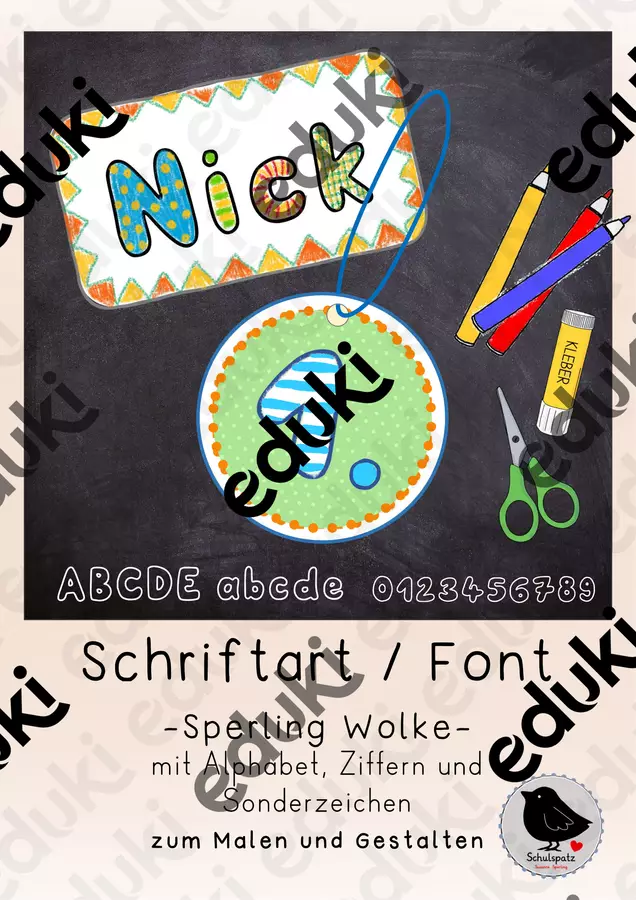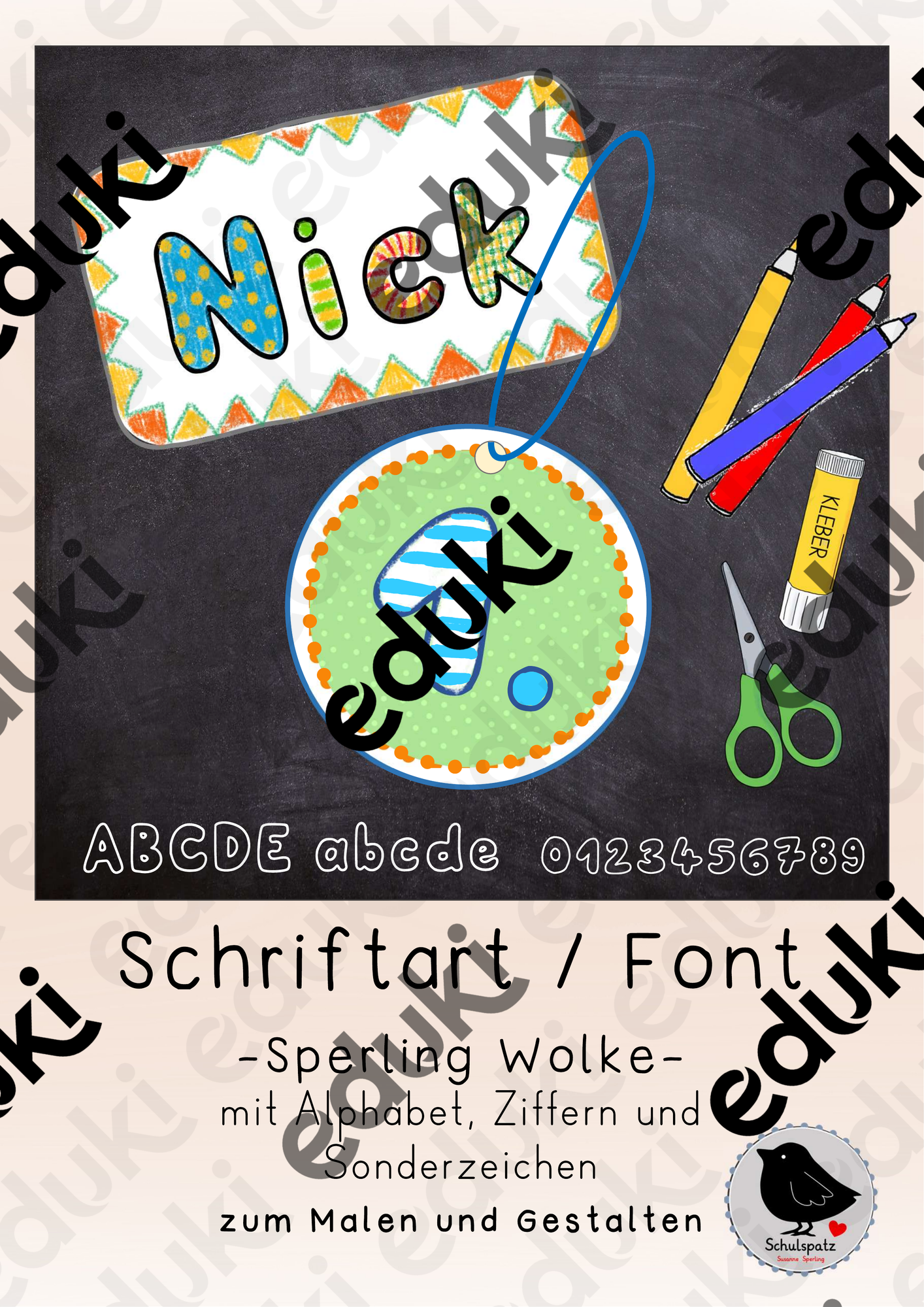
Mit dieser Schrift kannst du viele ansprechende Materialien erstellen, Arbeitsblätter entwerfen oder auch Plakate für den Klassenraum gestalten.
Setze sie ein im Kunstunterricht, lass die Kinder ausmalen, Muster entwerfen, Namensschilder gestalten etc. Im Anfangsunterricht können sie die Buchstaben ihres Namens ausmalen, ausschneiden und aufkleben.
Außerdem findest du einige Tipps und Tricks, wie du die Schrift für deine individuelle Gestaltung noch verändern  kannst.
Schriftart / Font zur Erstellung von Materialien